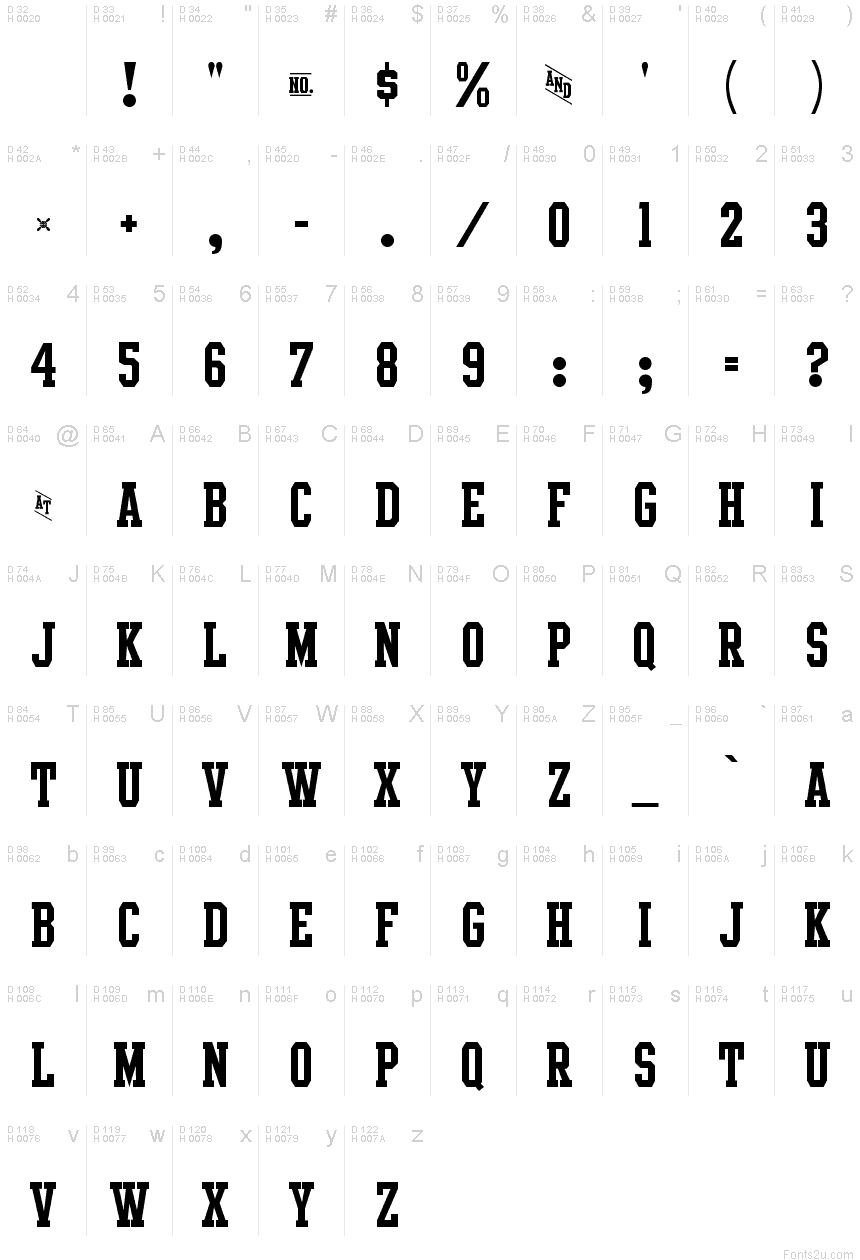
Intramural JL de Jeff Levine & Ray Larabie es una tipografía slab serif de estilo deportivo con esa actitud clásica de los equipos universitarios. Sus letras altas y comprimidas se apilan como las gradas de un estadio, mientras que sus remates cuadrados impactan con una precisión robusta, casi militar. El resultado recuerda a las pancartas vintage de gimnasio y a los números de los uniformes: un estilo sonoro, sólido y diseñado para destacar desde el otro lado del campo.
Con Intramural JL, tus titulares cobrarán vida al instante en carteles deportivos, logotipos de equipos, folletos de torneos, ropa escolar y eventos de temática retro. También luce espectacular en diseños de ropa y composiciones con muchos números. Combina esta fuente gratuita con una sans serif limpia y discreta para el texto principal, y deja que Intramural JL se encargue de llamar la atención en la parte superior.